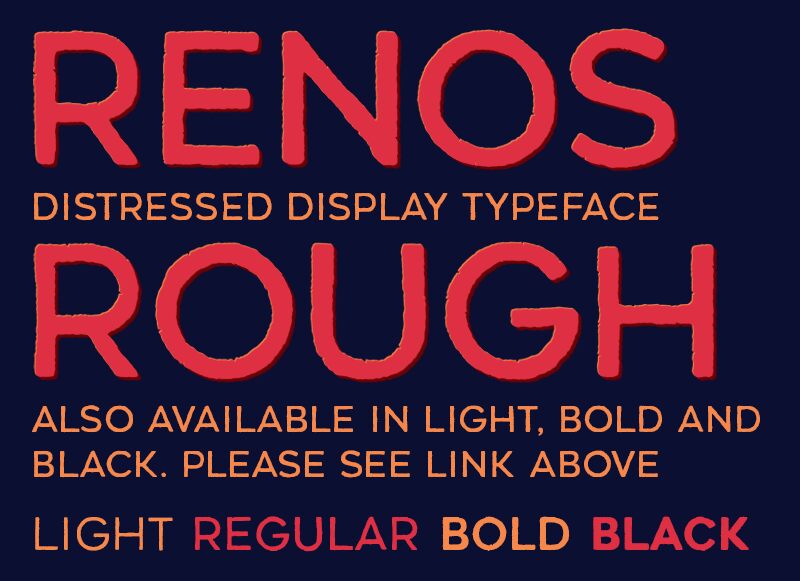
Reno Rough to font typu display o surowym, rustykalnym charakterze, zachowujący jednocześnie wyraźny geometryczny styl. Jest darmowy do użytku osobistego. W przypadku wykorzystania komercyjnego prosimy o wpłatę 18 $ przez PayPal, klikając przycisk „Donate to author” znajdujący się pod linkiem do pobrania. Otrzymasz wiadomość e-mail z potwierdzeniem zakupu licencji. Kroje Renos Rough są również dostępne w wielu wariantach grubości, które można nabyć tutaj: https://www.myfonts.com/fonts/deepak-dogra/renos-rough/
Renos Rough
Deepak Singh Dogra